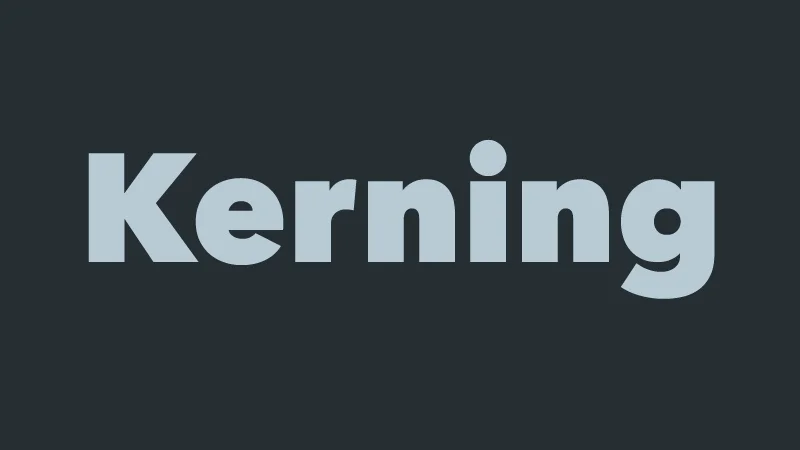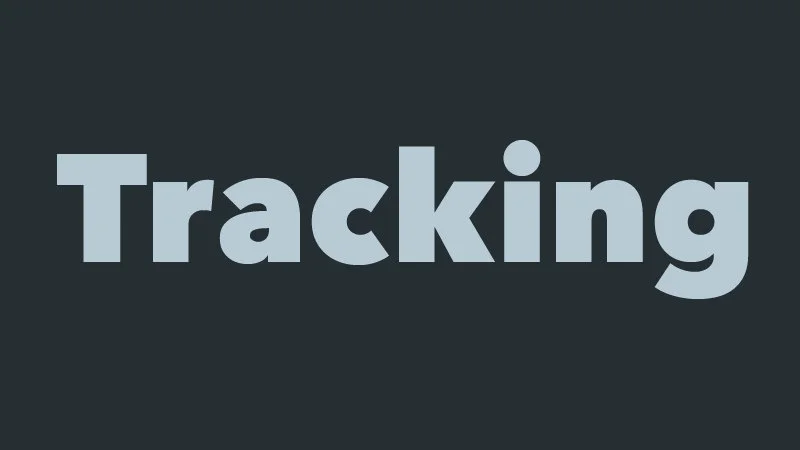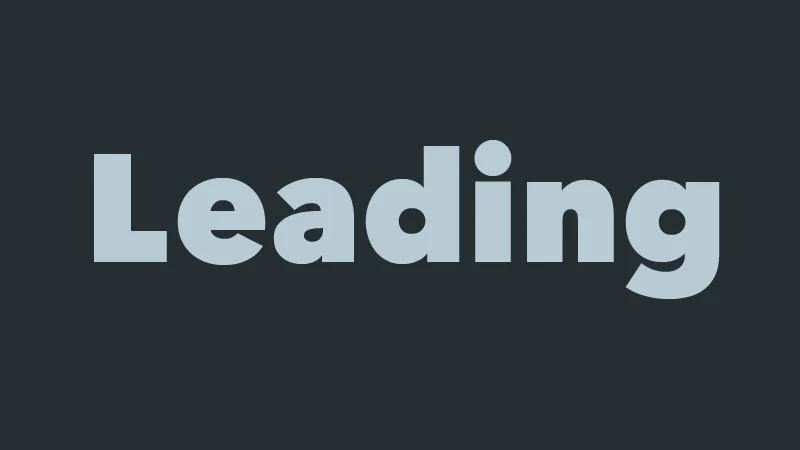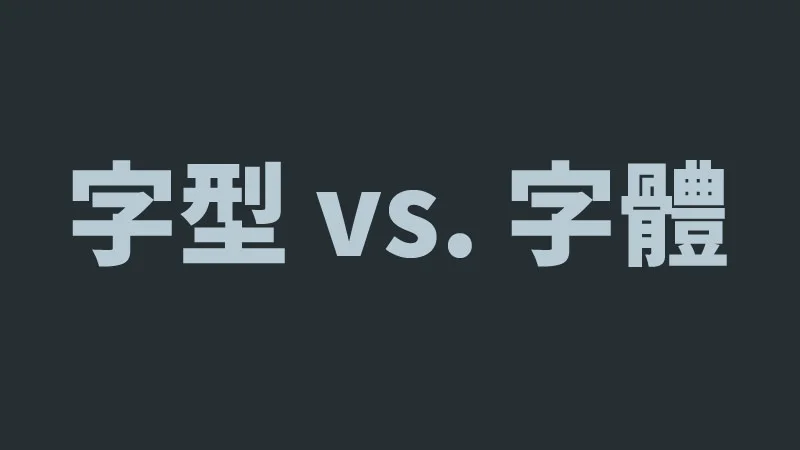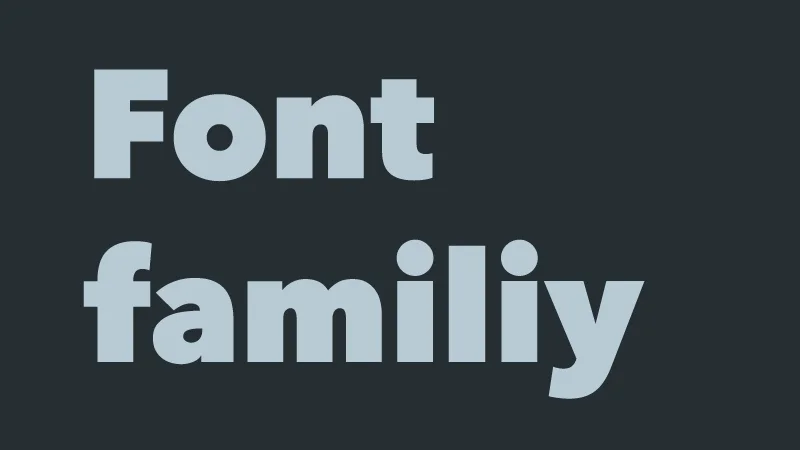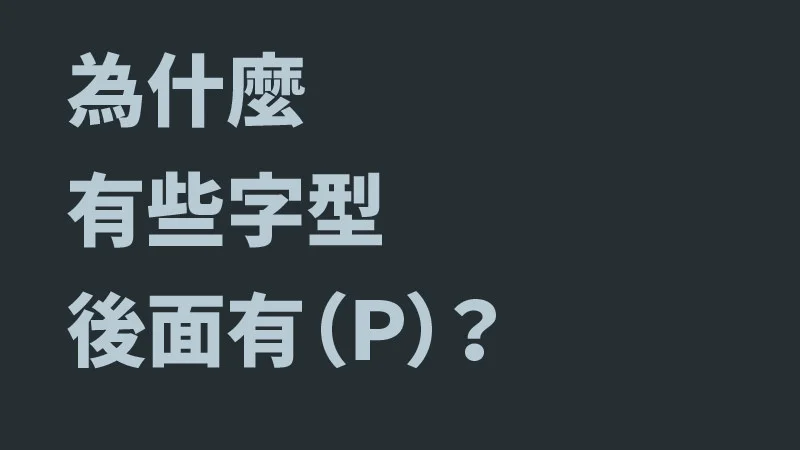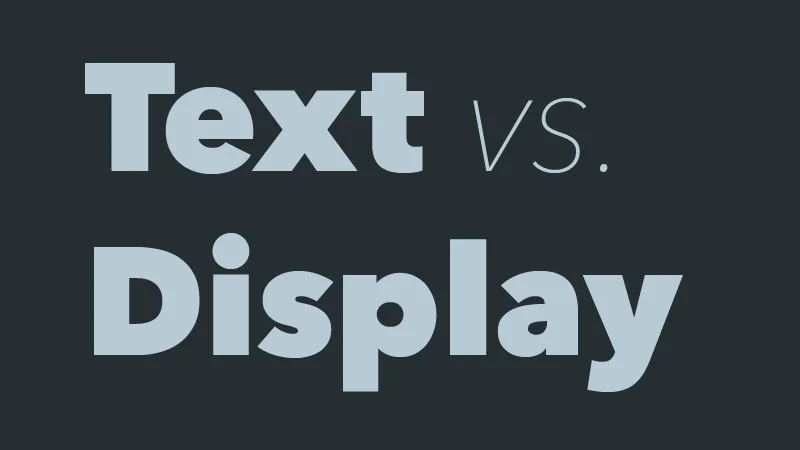
給設計初心者:字型基礎八篇
在這兩年推廣字型的過程中,我們發現字型與版面編排其實是一把鑰匙,打開視覺設計的大門。厲害的設計師對字體絕對不馬虎,他們了解文字並不只是資訊的載體,在版面上也是視覺的元素。理解字型與版面編排,就等於掌握了視覺傳達的核心概念。justfont 今年初上線的微型內容網站 jf tips 近兩個月來開始推出「新手村」系列文章,從最基礎的字型知識開始帶設計初心者進入這個領域。我們在這裡匯整、引薦其中八大主題給需要接觸基本視覺設計的初心者。
保持距離之必要:Kerning
Kerning 雖然是老梗,但無論怎麼強調也不為過。不僅包含了好不好讀也包含了好不好看。學習掌握空間的距離與比例關係,是學習學習視覺設計的第一步。Kerning 不止出現在英文,就連中文也有需要 Kern 的地方。其實,控制距離的功夫不管對哪一種語言來說都很重要。這也可以讓我們了解到文字在版面上其實是圖像的一環,不僅僅是表達資訊的載具而已。
說話的語氣:Tracking
語氣也能轉化為排版樣式。當文字距離比較開的時候,好像在慢慢說話,反之,則有一種緊迫的感覺。《字型之不思議》提到有些品牌之所以有高級感,很重要的因素是文字的間距展現了大人一般從容不迫的說話口吻;我們也發現很多潮牌,例如 Superdry,就喜歡壓縮文字間距帶來完全不同的感受。為什麼只是文字距離的不同,就可以帶來這麼大的變化呢?
讓文字呼吸:Leading
Typography 這門學問,很大一部份有關於空間的配置。行距是讓文字呼吸的空間。它能讓讀者的眼睛認為文字有方向,而不是一坨黑黑的東西。這就是 Typography 一直很要求的 Readability(可讀性)。但你知道行距是怎麼來的嗎?不同的字體要設不一樣的行距嗎?看起來只是取個空間,但其中可是大有學問喔。
差一個字就不一樣:字型 vs. 字體
字型跟字體有什麼不一樣呢?為什麼我們有分清兩者的必要呢?其實是這樣的,人類很早以前就有字體,但是有字型還是很近代的事情。特別是能供個人任意選用的字型產品,更是最近三十年的事情呢。雖然在日常生活的溝通情境中,這兩個字的意義與內涵可以是互通的,但是有基本的差異在。立志成為專業設計師的你,也要了解一下喔!
區隔得一團和氣:字型家族
一團和氣,但又各自獨立,有這樣的東西存在嗎?有。字型家族就是這樣的事情。這不是八點檔劇名。它是 font family 的直譯,一個非常有用的排版發明。成員都很獨特,但又能相互搭配得家和萬事興。他們有相近的基因:骨架、裝飾部分、氣質等等,都很相近,只是粗度或樣式的不同(樣式指的是例如正體、斜體的不同)這樣就能各司其職,又能合作無間。配備廣大字型家族的產品也是挑選字型的一個面向,會讓設計師省去許多搭配的麻煩。
藏在小細節裡的重要知識:為什麼有些字型後面有(P)?
這是一個看起來不重要,但其實背後大有玄機的東西,可以讓我們學到關於歐文字型的重要知識。P 可不是隨便亂取名的。它的意思是 Proportional,與 monospace 是相對概念。中文字型內建的歐文字型常常良莠不齊。字型廠商常常為同一套中文字型出產兩種不同版本,一個是後面有 (P) 的版本,一個是普通的版本。它們的差異,其實不在中文,而在歐文英數上面。
各有各的長處:內文字型 vs. 展示字型
在眾多字型產品裡,可以粗成兩種:用於內文的「內文字型」與裝飾性用途,通常用於標題等展示用途的「展示字型」。兩種字體主要差別是什麼呢?其實就是使用情境。內文字型用於長時間的閱讀,講究均值平穩的特性。要讓讀者埋首苦讀數小時,仍然能沈浸其中,眼睛也還是很舒服的字型。展示字型不一樣,通常因為是標題、招牌大小,字體比內文大數十、數百倍。它要能抓住目光,要吵鬧,而且最好要有味道。
都是心血(血汗)結晶:中文字型是怎麼設計出來的
「字型」不是從電腦裡噴出來的嗎?的確有人問過這個問題。翻譯成白話就是「字型不是電腦自己產生的嗎?」當然不是。這樣認為的話,字型設計師們情何以堪呢?字型這種東西,一筆一畫都是工藝的心血結晶啊。不論是一筆一畫的描繪,還是用筆畫組件自動拼裝成字型,字型設計都是很漫長的過程。上萬個字要保持一致的品質,是最考驗中文字型設計師的功夫。